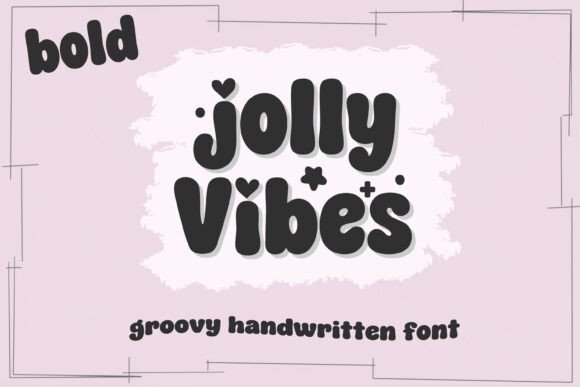
Jolly Vibes Bold
POD(μ£Όλ¬Έν˜• 인쇄) μ œν’ˆ, κ²°ν˜Όμ‹ μ΄ˆλŒ€μž₯ λ˜λŠ” μ†Œμ…œ λ―Έλ””μ–΄ κ·Έλž˜ν”½μ„ λ§Œλ“€ λ•Œ Jolly Vibes BoldλŠ” 이상적인 μ„ νƒμž…λ‹ˆλ‹€.